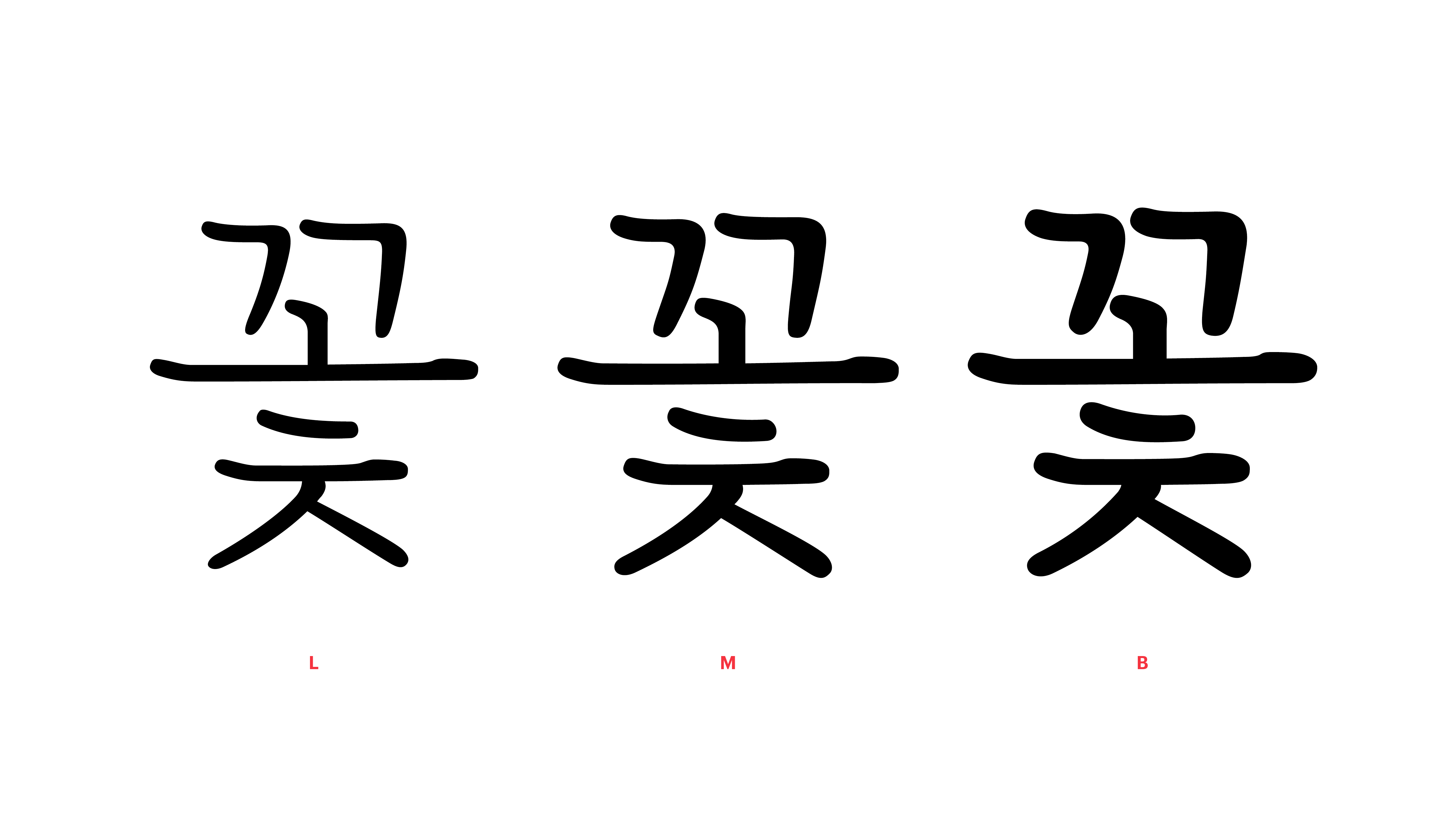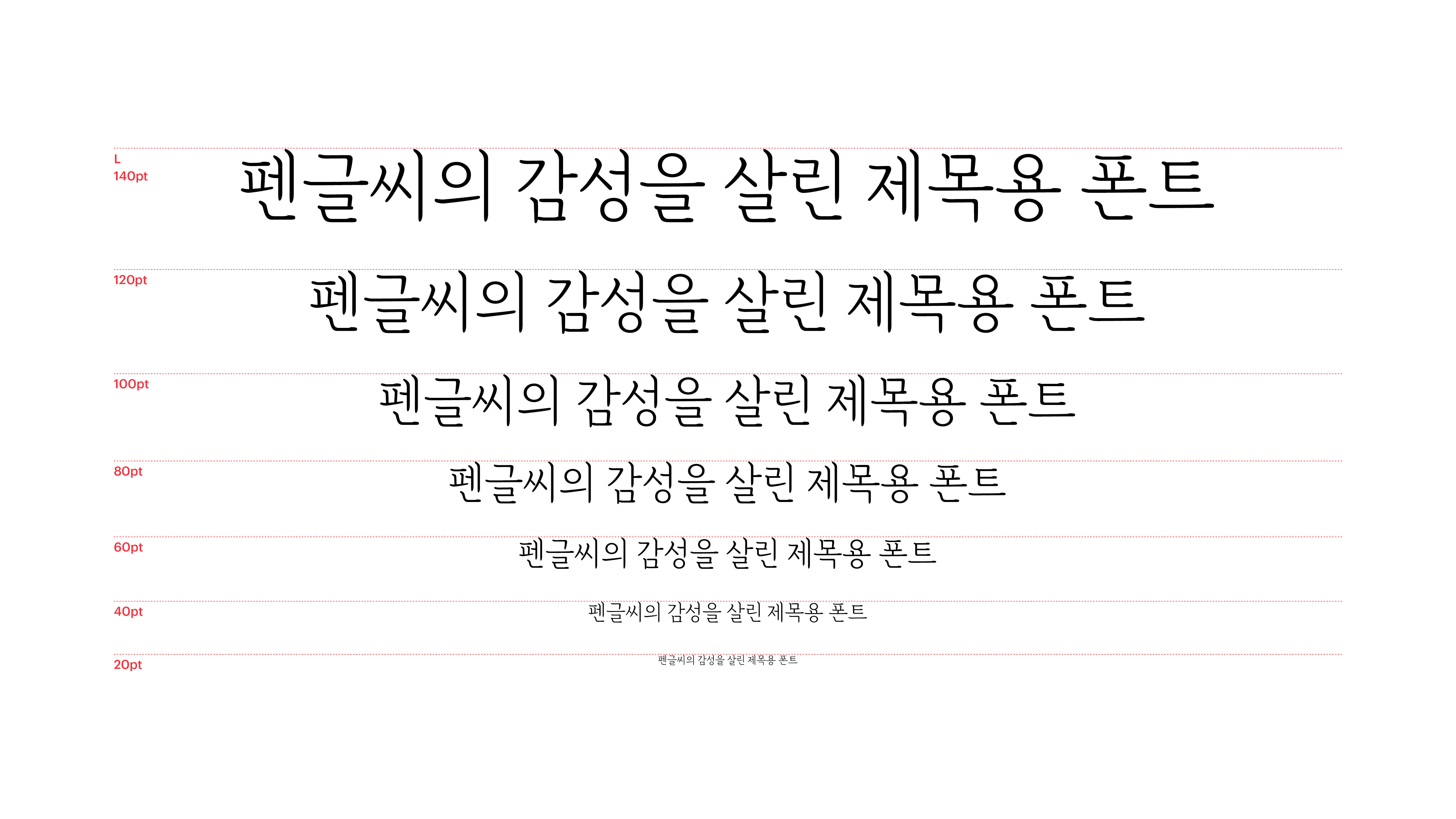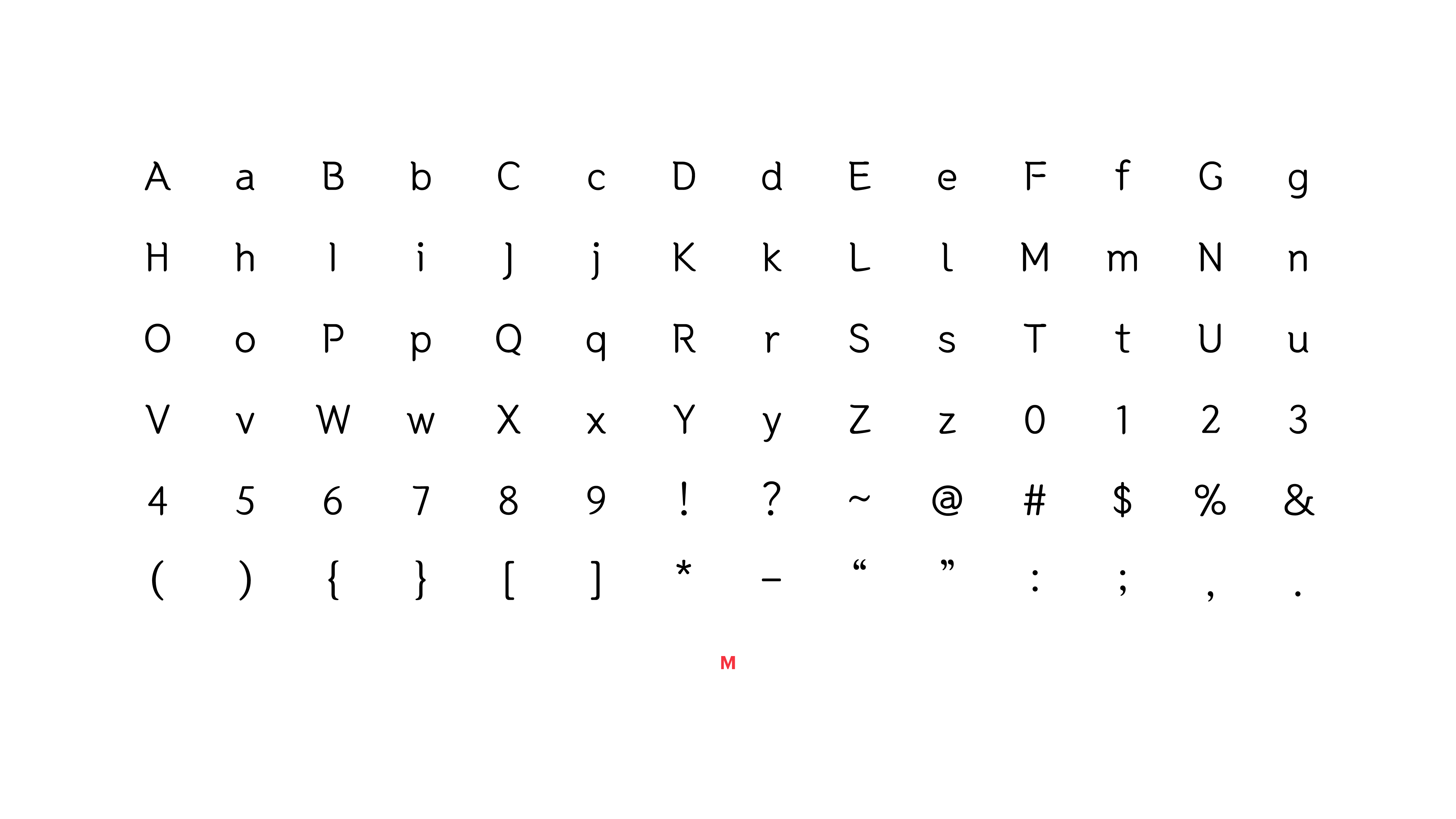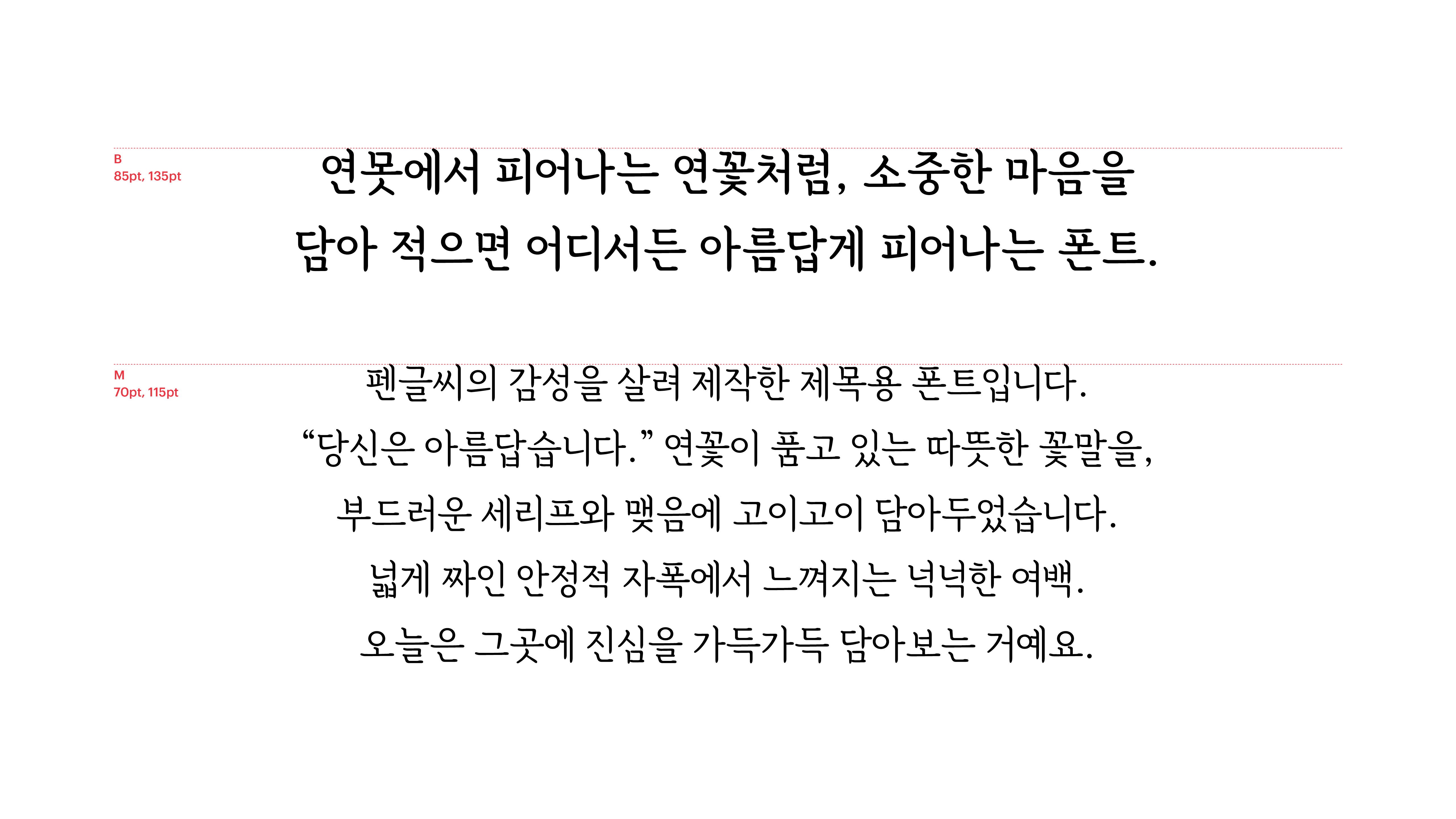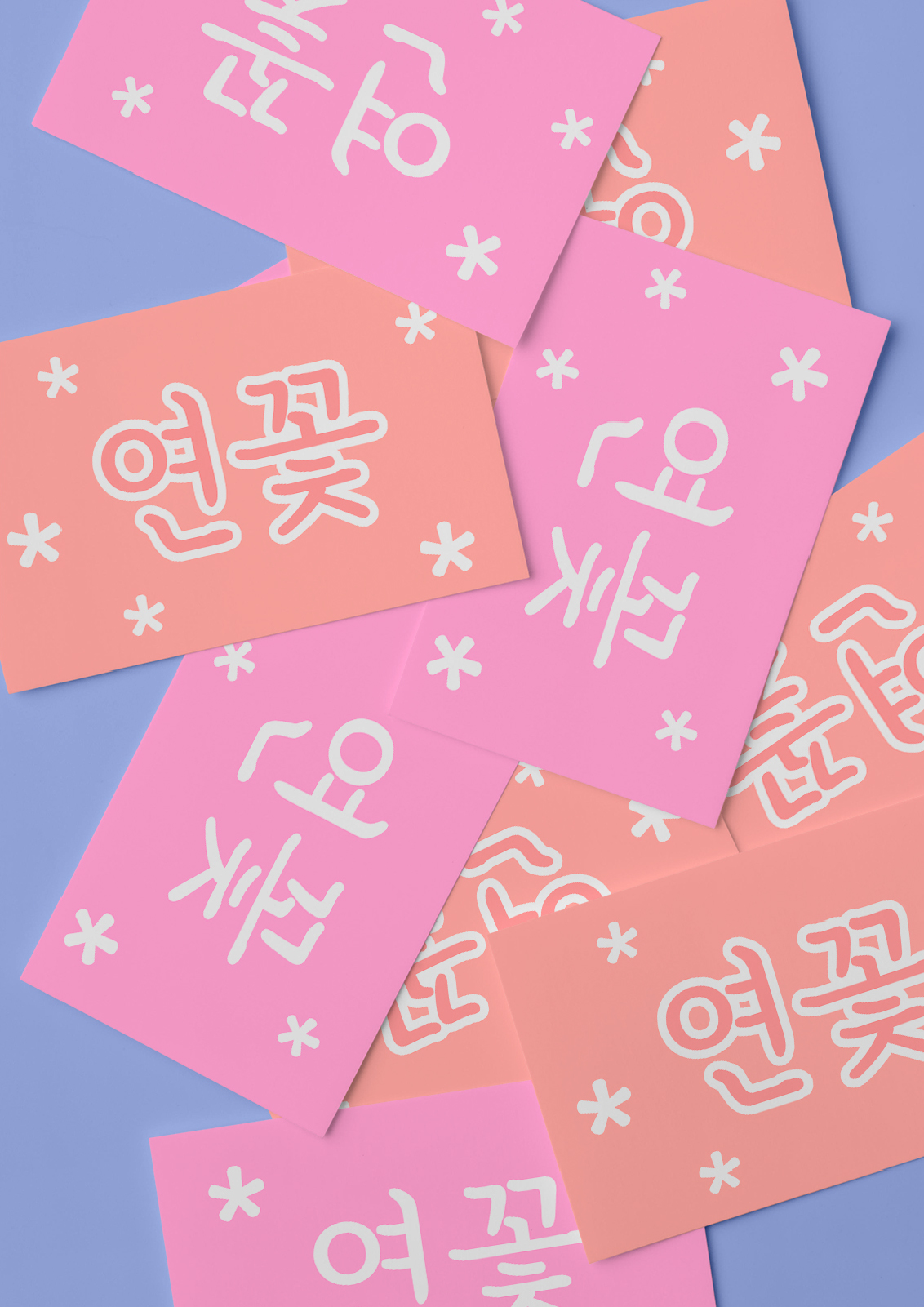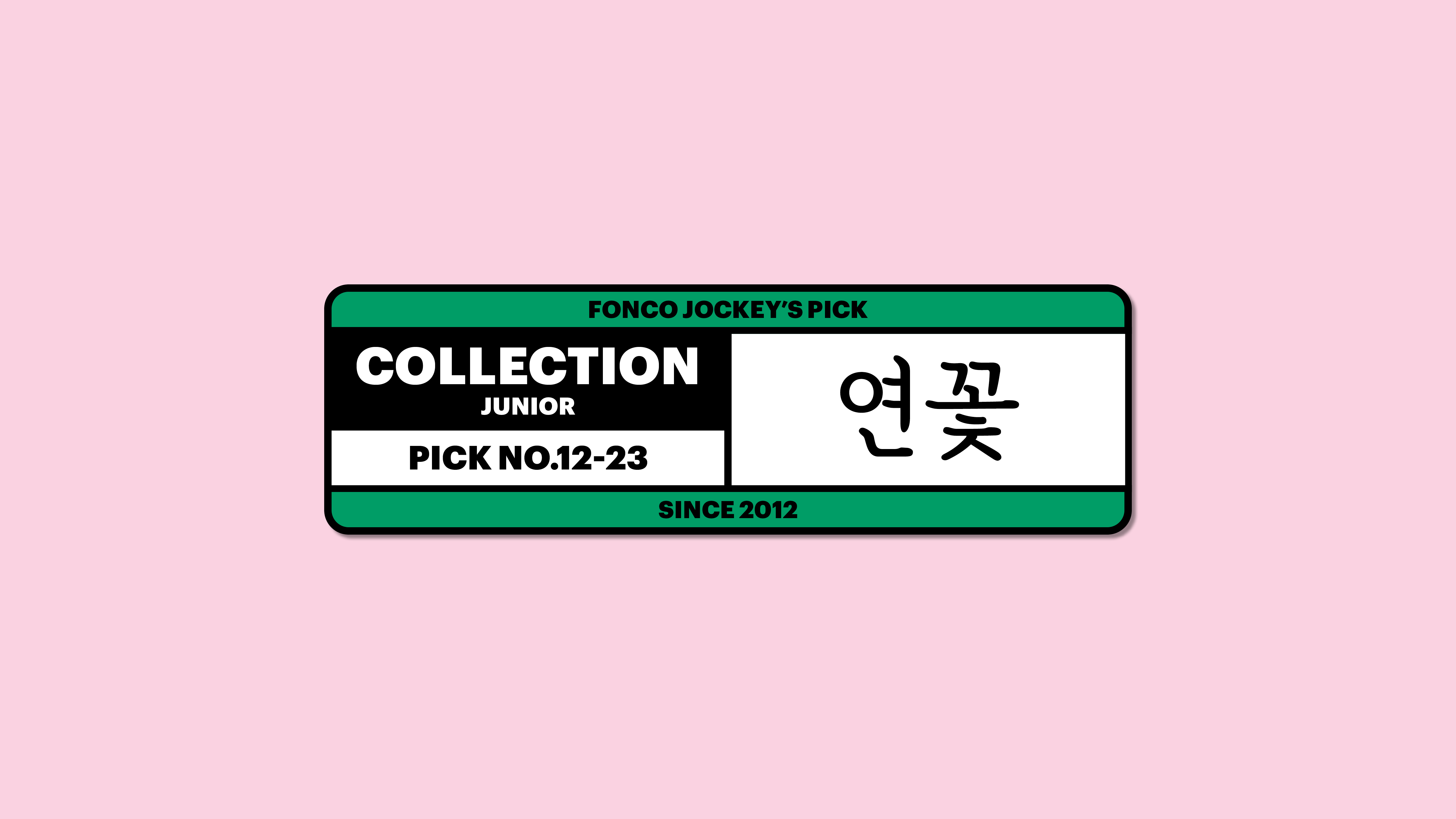
[손글씨]
연꽃
Yoon 연꽃
펜글씨의 감성을 살려 제작한 제목용 폰트입니다. “당신은 아름답습니다.” 연꽃이 품고 있는 따뜻한 꽃말을, 부드러운 세리프와 맺음에 고이고이 담아두었습니다. 넓게 짜인 안정적 자폭에서 느껴지는 넉넉한 여백. 오늘은 그곳에 진심을 가득가득 담아보는 거예요.